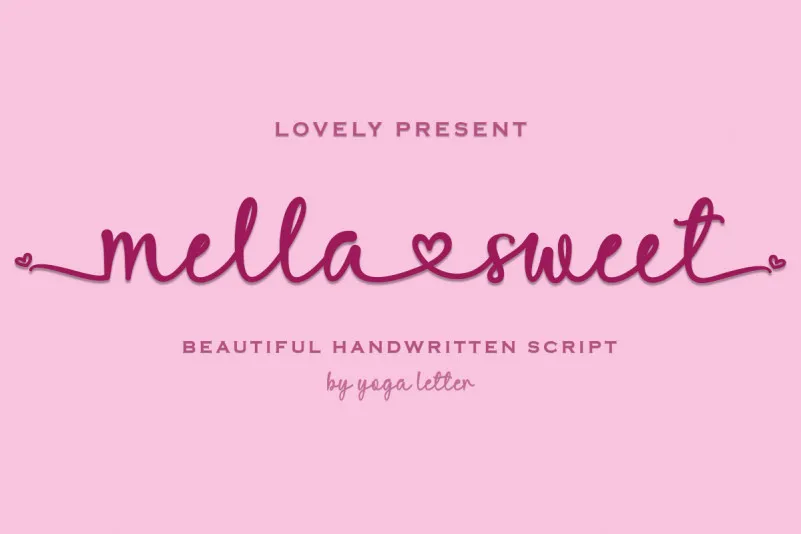
A Mella Sweet Font é uma aquarela fluida que captura o encanto do seu nome. Inspirada no círculo suave da letra “M”, esta fonte script cria um ambiente de elegância e tranquilidade, perfeita para trabalhos onde deseja transmitir charme e conforto visual, como cartões de aniversário personalizados ou gráficos publicitários em ambientes comerciais. Como uma filha adorável da letra “M”, a Mella Sweet não apenas expressa cuidado e consideração, mas também uma sensação de familiaridade que faz qualquer texto se sentir acolhedor. Inspirada no estilo de escrita fluido das fontes de script mais românticas, a Mella Sweet oferece um toque suave e delicado para qualquer design. Ideal para aqueles designers gráficos em busca de um contraste entre o tradicional e o moderno, ela é uma escolha perfeita para quem deseja criar algo ligeiramente diferente no ambiente digital ou impresso.